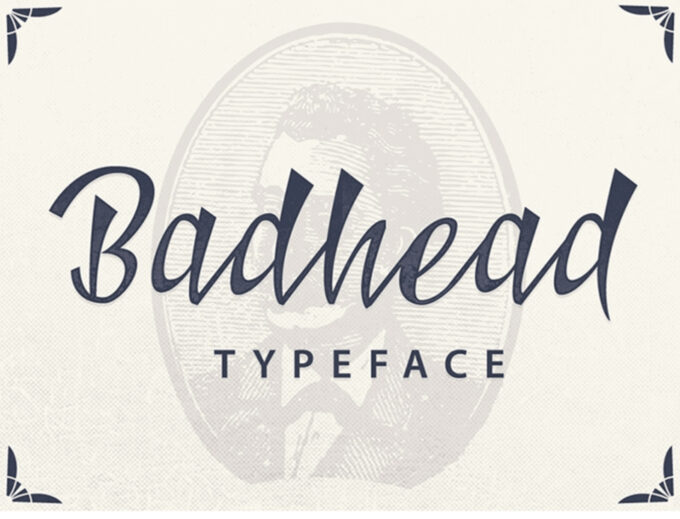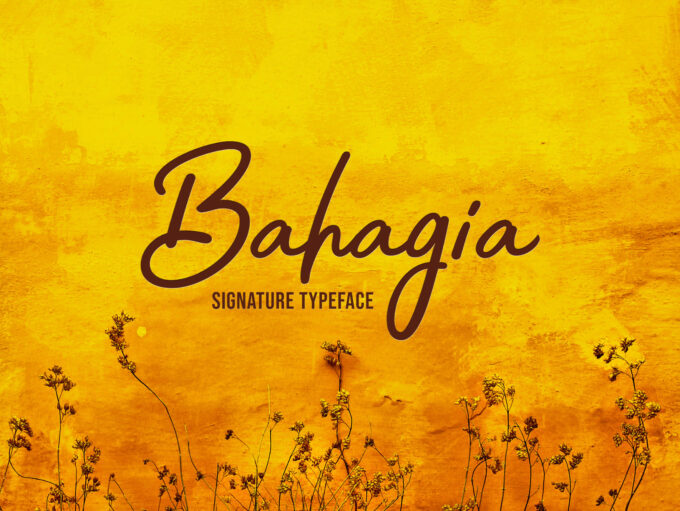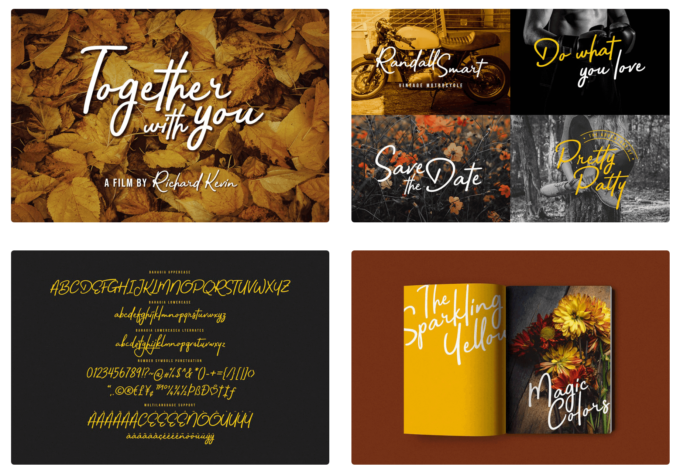
【全て無料】滑らかで美しい筆記体のフリーフォントをまとめて紹介!!
今回は滑らかで美しい『筆記体フォント素材』を紹介していきます。
ぜひお気に入りのフォントを見つけてデザインに生かしましょう!!
HIGHLANDER MARKER
Oh Wonder Font Duo
Jumper Handwritten Font
Delight Lettering
Nickainley
Redlight Script
NORTH AVELLION
CONNOISSEURS
BADHEAD
Free Barokatt Script Font
Rockville Brush Font
EMMELINE
Bahagia
Signatura Monoline
Santana
Larquette Typeface
Streetlight
Breakable Free Typeface
Frutilla Script Free Typeface
Alentine Script Font
Cinderella
Brotherina Script Font
Reshuffle Script Free Demo Font
Antro Vectra Script Font
Angel Tears